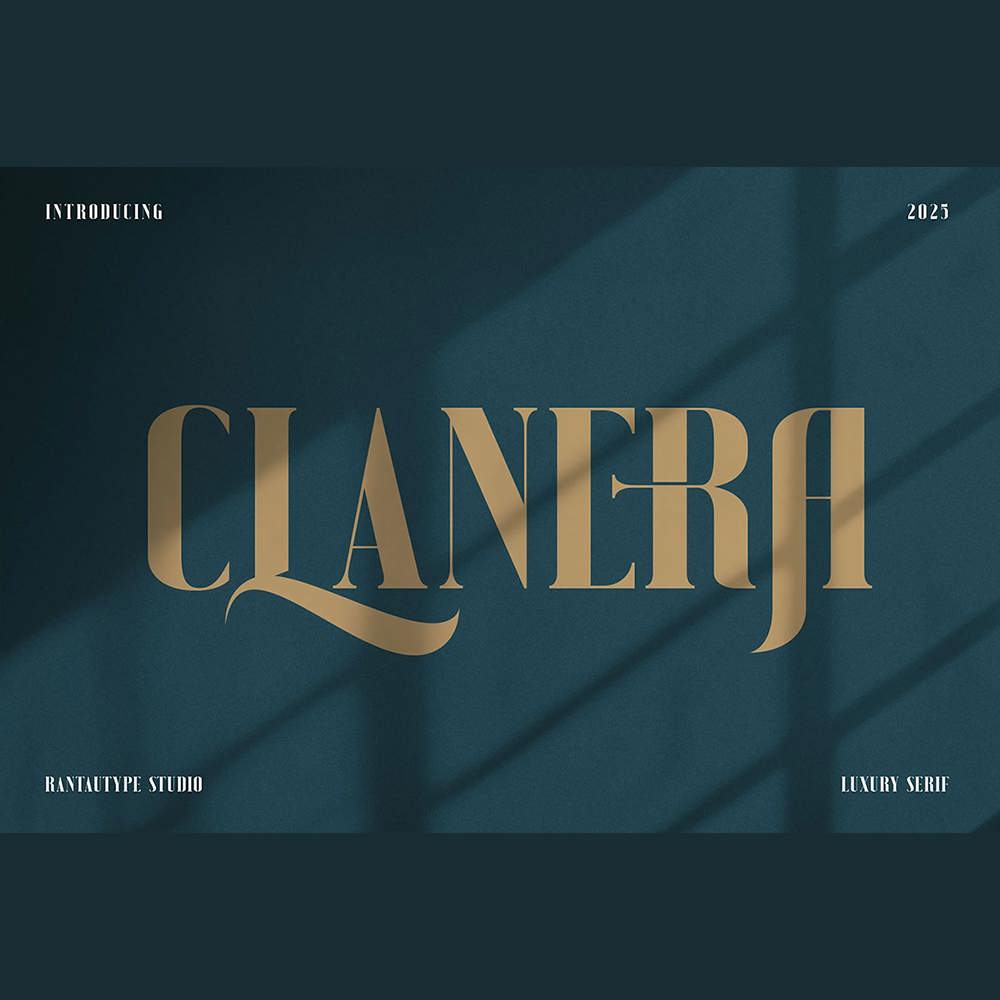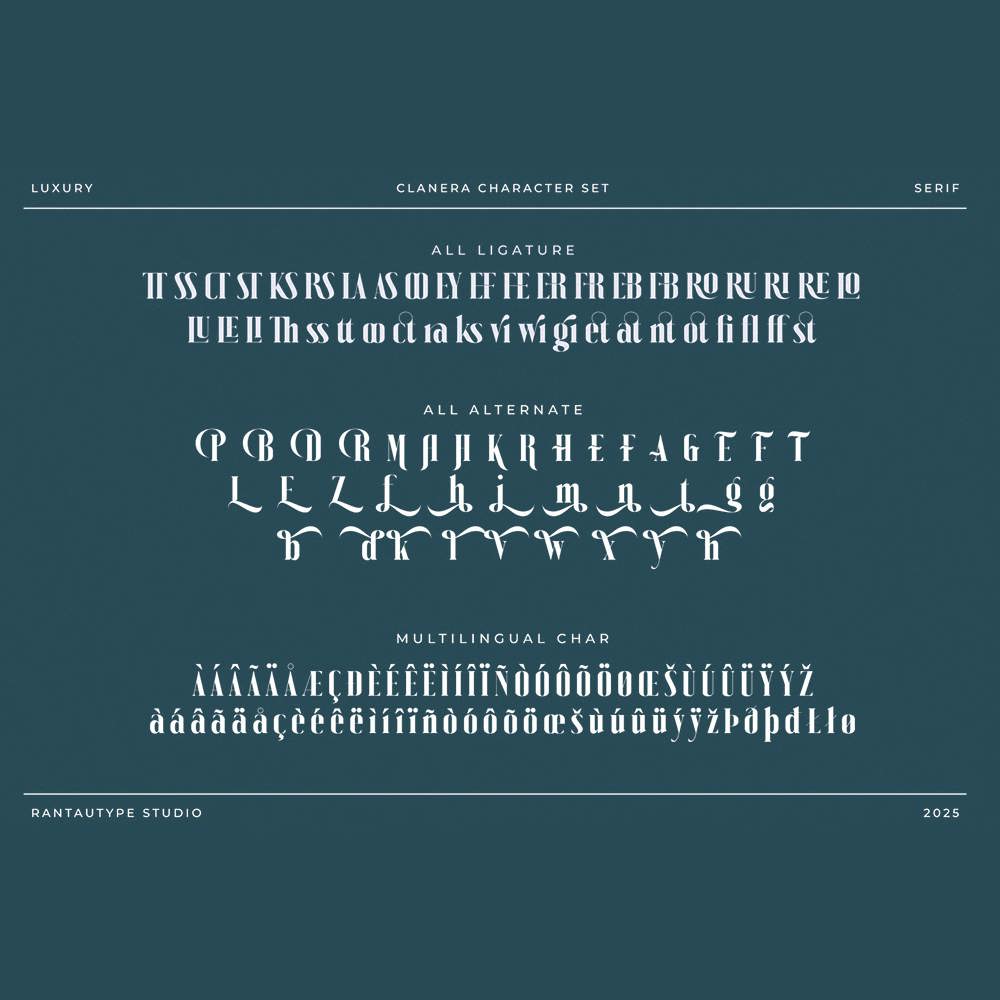
دانلود فونت انگلیسی Clanera Font
فونت پرمیوم و انگلیسی Clanera Font یک فونت سریف جسورانه، مینیمالیستی و مجلل است. Clanera دارای یک لیگاتور زیبا و جایگزین برای برجسته کردن پروژه های طراحی و انتخابی عالی برای هرگونه فعالیت خلاقانه، طراحی شیک و زیبا در سبک طراحی لوگو، تبلیغات، عکاسی، پروژه برندسازی، مجله، طرح تجاری تبلیغاتی، مفهومی و بسیاری از پروژههای دیگر با کمی ظرافت است.